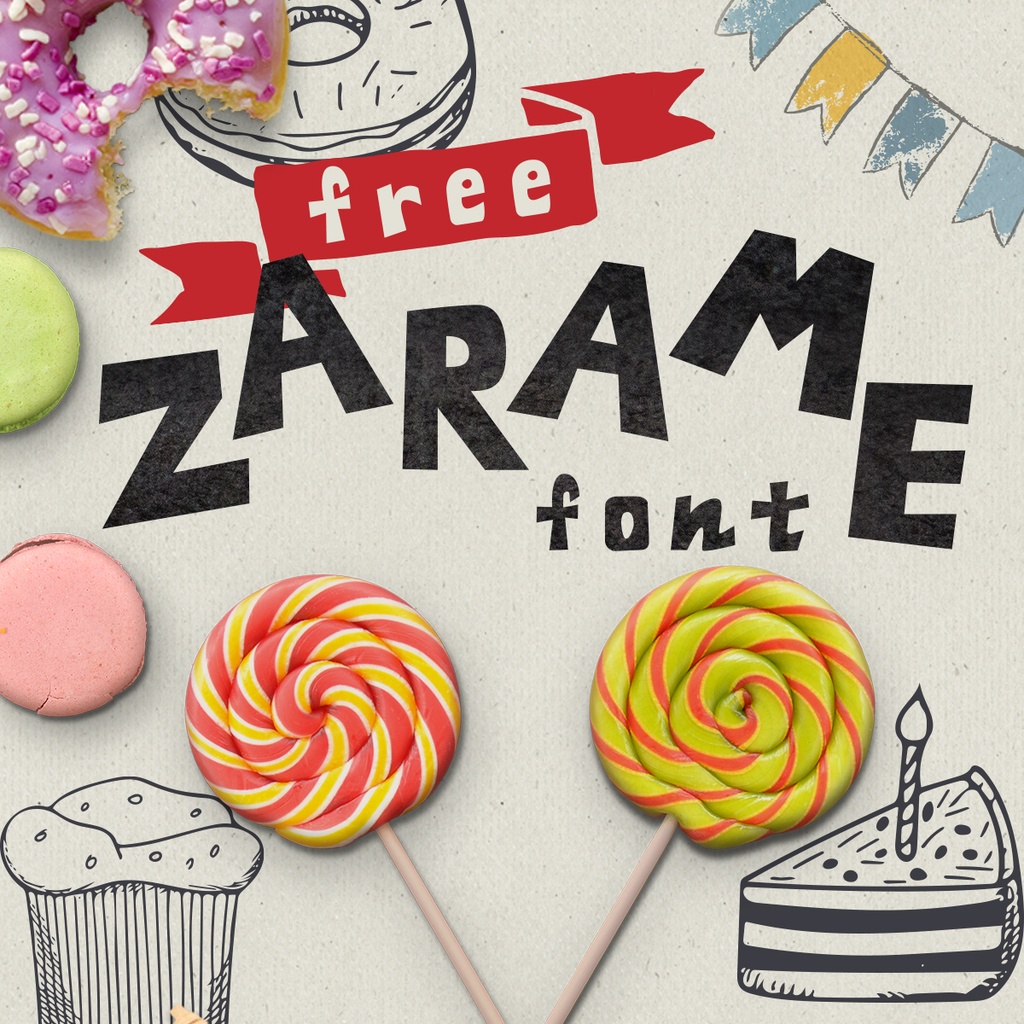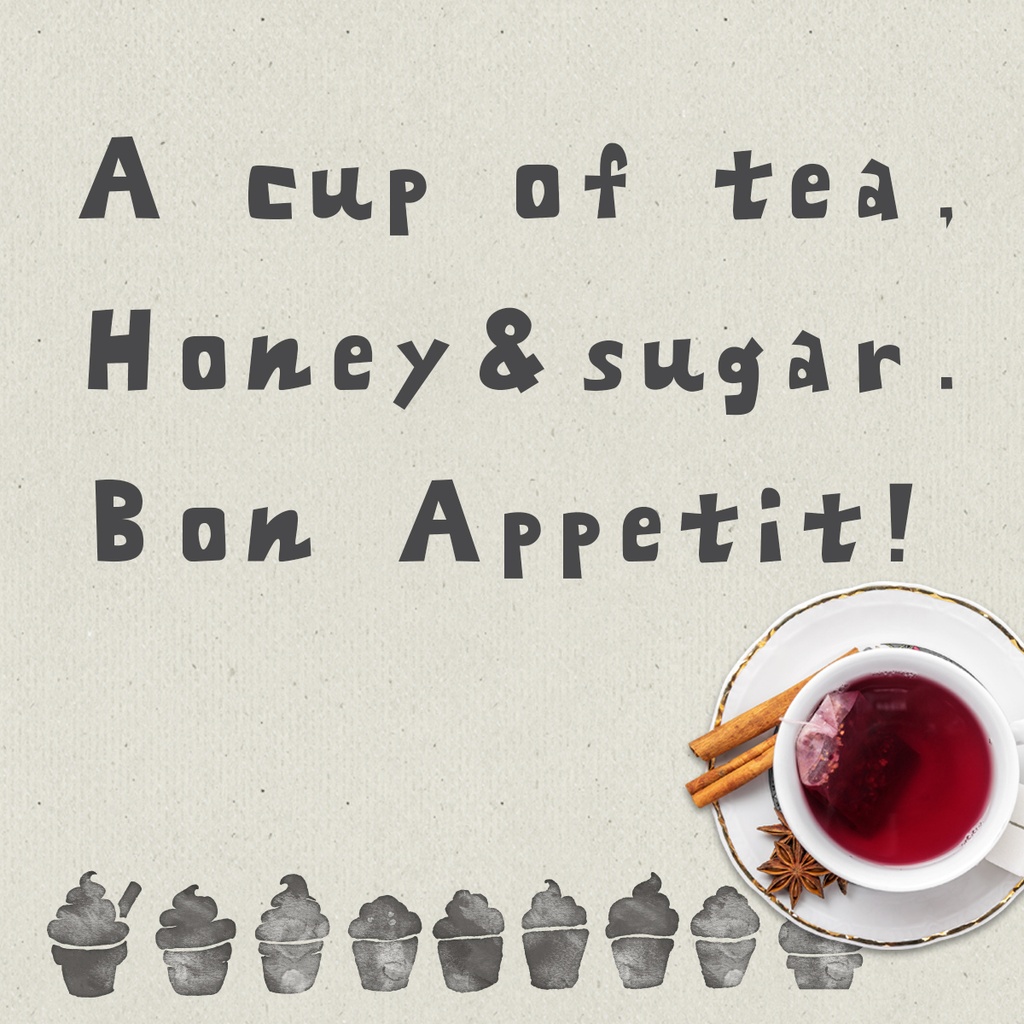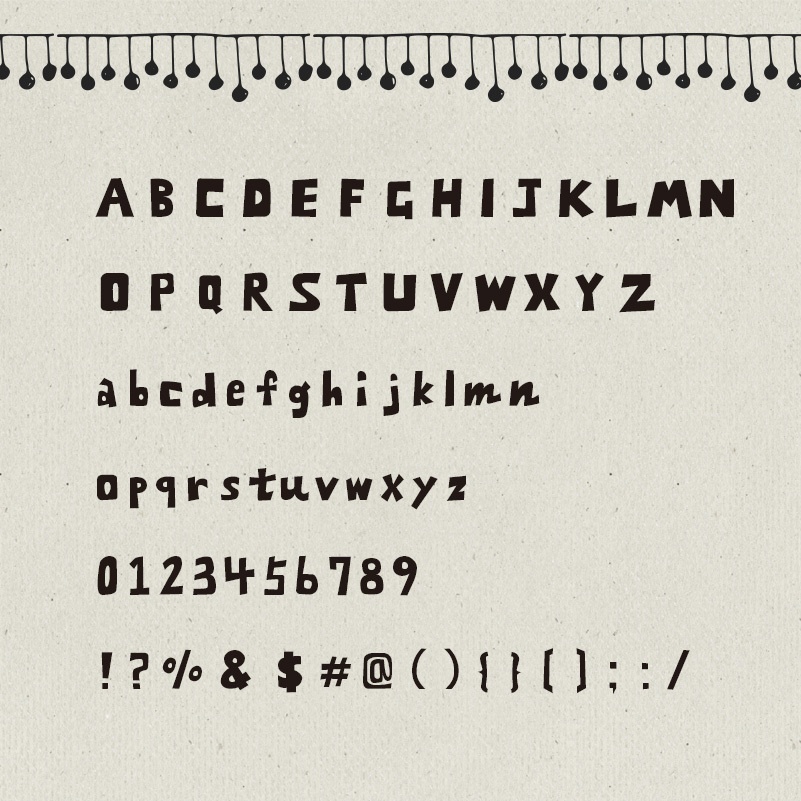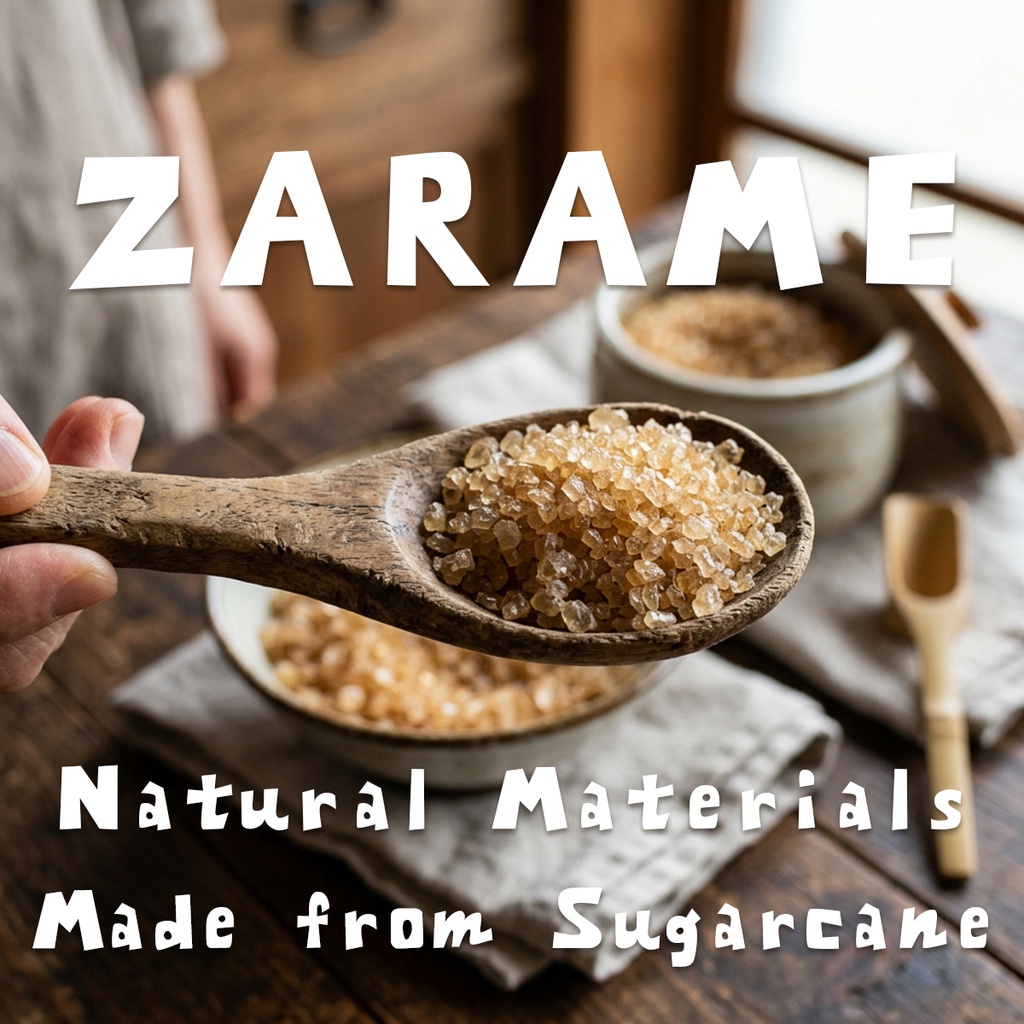
【商用可・無料 お試し版】ざらめフォント(フリーフォント)手書き風フォント お菓子づくりにかかせないザラメ糖をイメージしたフォント。 手書きの風合いのある少し太めのラインで作りました。 見出しや目立たせたいところに。 同人誌・SNS・動画・WEBデザインなど幅広い用途にお使いいただけます。 どの角も丸みをおびたやさしいフォルムが特徴です。 商用利用OKです。 アルファベット・記号 収録 フォント形式:OpenTypeフォント 【動作環境】Windows / Mac 対応 【インストール方法】 Windows:ダウンロードしたZIPを解凍し、.otfファイルを右クリック→「インストール」 Mac:Font Bookにファイルをドラッグ&ドロップ ▼ひらがな・カタカナ版も販売中!(¥190)→ https://vanillabeanz.booth.pm/items/714819 【利用規約】 ・個人・商用利用ともにご利用可能です。 ・ご利用にあたってクレジット表記の必要はありません。 ・フォントの著作権は、放棄しておりません。 ・ご使用によるトラブルや損害等、一切の責任を負いませんのでご了承ください。 下記の事項でご利用いただけます。 1. WEB・印刷物へのデザインに使用 2. WEBフォントとしての利用 3. 販売用物品への使用 4. ロゴへの使用(商標登録は不可) (※ご不明な場合は、お問い合わせください。) 下記の事項でのご利用は不可とさせていただきます。 1. フォントデータの販売 2. フォントデータの再配布 3. 商標登録 4. 公序良俗に反するものへの利用